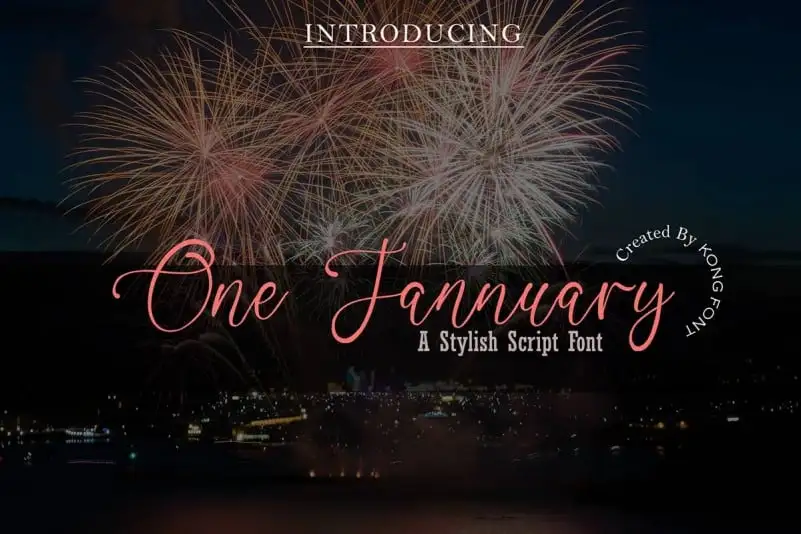
One Jannuary Calligraphy Font – Download Grátis
A One Jannuary Calligraphy Font é uma escolha perfeita para designers apaixonados por letras elegantes. Seu traço delicado e fluido, criado pelo designer fontkong, se destaca como um belíssimo script font. Este recurso gráfico perfeito combina elegância com versatilidade, ideal tanto para headlines quanto para blocos de texto que apresentam variabilidade entre o máximo e o mínimo. Ideal para uso em sites, impressões, vídeos ou qualquer outra aplicação visual, a One Jannuary Calligraphy Font trará um toque singular e arrojado. Seja você criando uma página web minimalista ou uma revista de moda elegante, essa fonte vai garantir que sua mensagem seja transmitida com estilo e sofisticação. Suas linhas suaves e fluidas complementam qualquer projeto visual, seja para um site de notícias informativo ou para um anúncio em alta sobre estilos de vida. A One Jannuary Calligraphy Font é definitivamente uma escolha que faz a diferença em seu trabalho gráfico.